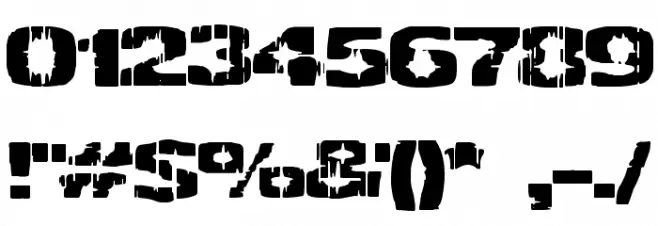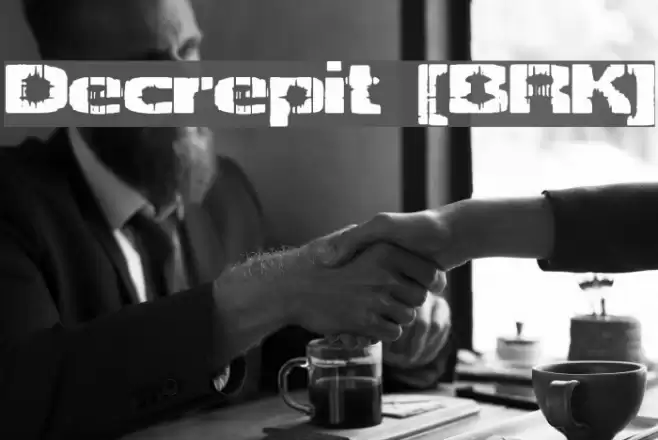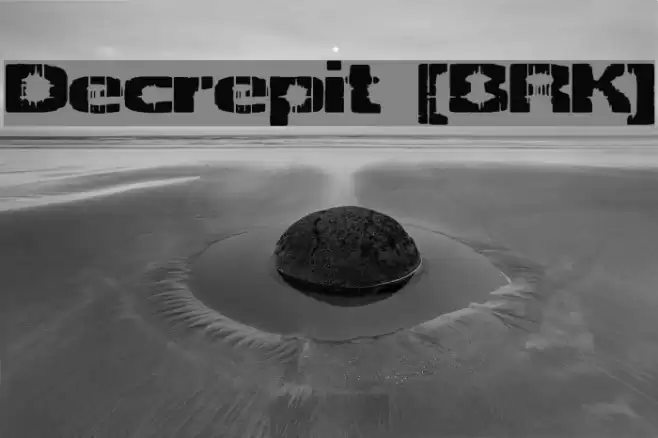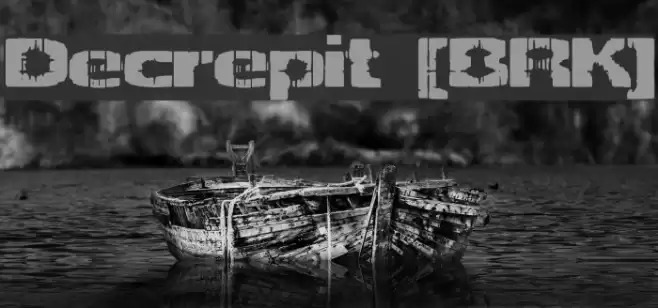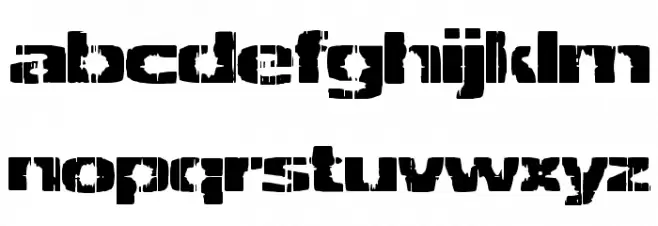
Decrepit [BRK] Font
| Projets proposés | Ideal for projects requiring a vintage or grunge aesthetic, such as posters, album covers, or themed event invitations. |